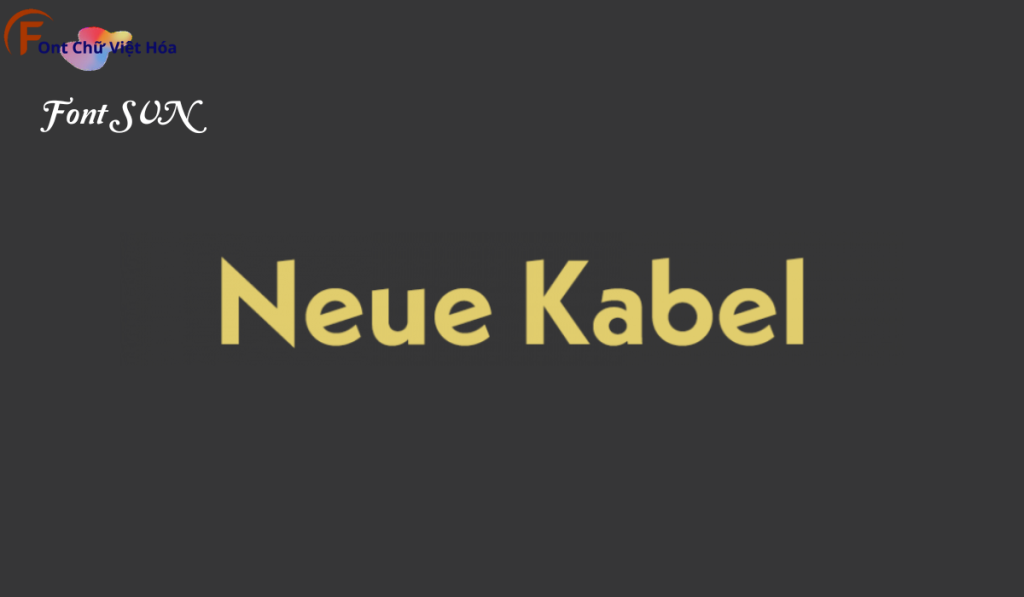
Font SVN Neue Kabel Việt Hóa
Tác giả: SVN Neue Kabel
Kiểu chữ: Sans-serif
Độ dày: Regular, Medium, Bold
Font SVN Neue Kabel Việt Hóa là một font chữ không chân hiện đại, thuộc bộ font SVN. Được thiết kế với mục tiêu mang lại sự tinh tế và thanh lịch, font này phù hợp cho các dự án thiết kế như website, tài liệu, và bao bì sản phẩm. Với các nét chữ rõ ràng và độ dày đều đặn, Font SVN Neue Kabel Việt Hóa không chỉ dễ đọc mà còn tạo cảm giác chuyên nghiệp. Việc Việt hóa font giúp người dùng dễ dàng sử dụng trong các thiết kế tiếng Việt, mang lại sự tiện lợi và thẩm mỹ cao.